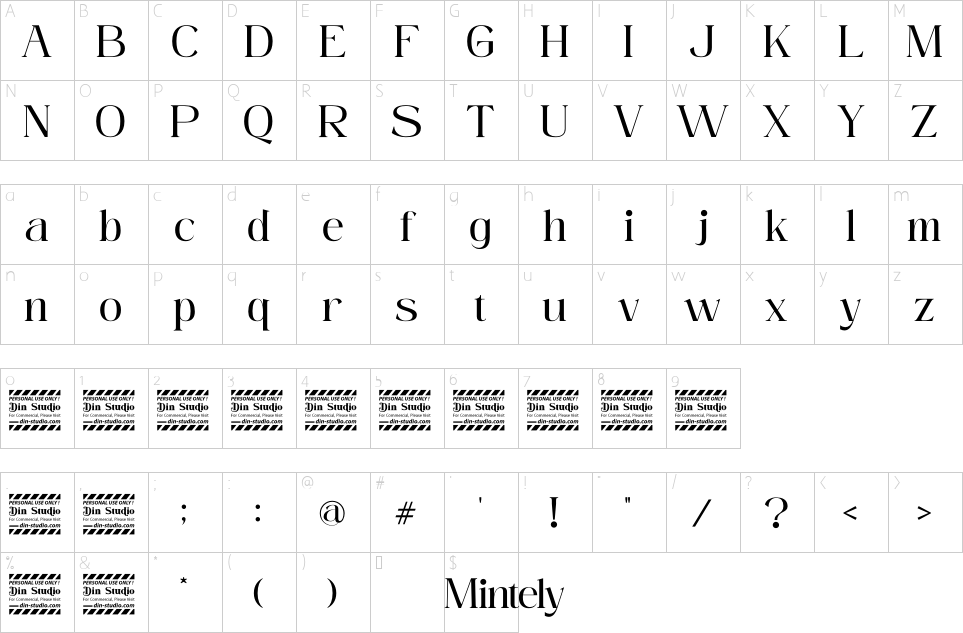
A Mintely é uma fonte elegante e agradável para uso em sites, revistas e materiais digitais. Lançada pela Din Studio, essa fonte foi projetada para complementar uma ampla variedade de projetos gráficos. Com sua tipografia fluida e moderna, Mintely proporciona um visual atraente e profissional a qualquer projeto. Com sua facilidade de uso em ambientes Windows e Mac, essa fonte garante que você possa incorporar personalidade e estilo em suas criações. Desenvolvida por designers experientes, Mintely já foi baixada por mais de 638 usuários, demonstrando sua eficácia e popularidade. Se você está procurando por uma fonte de qualidade, com uma aparência atraente e fácil de usar, Mintely é uma opção a ser considerada.